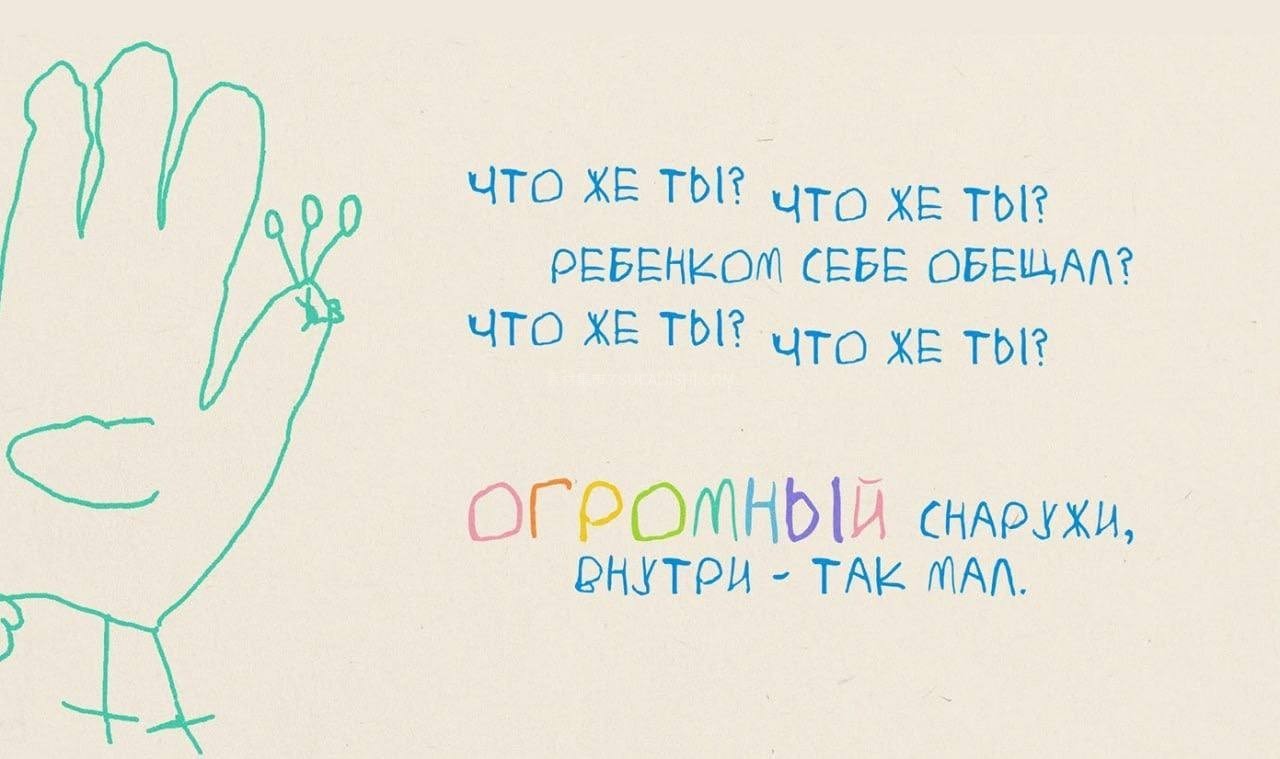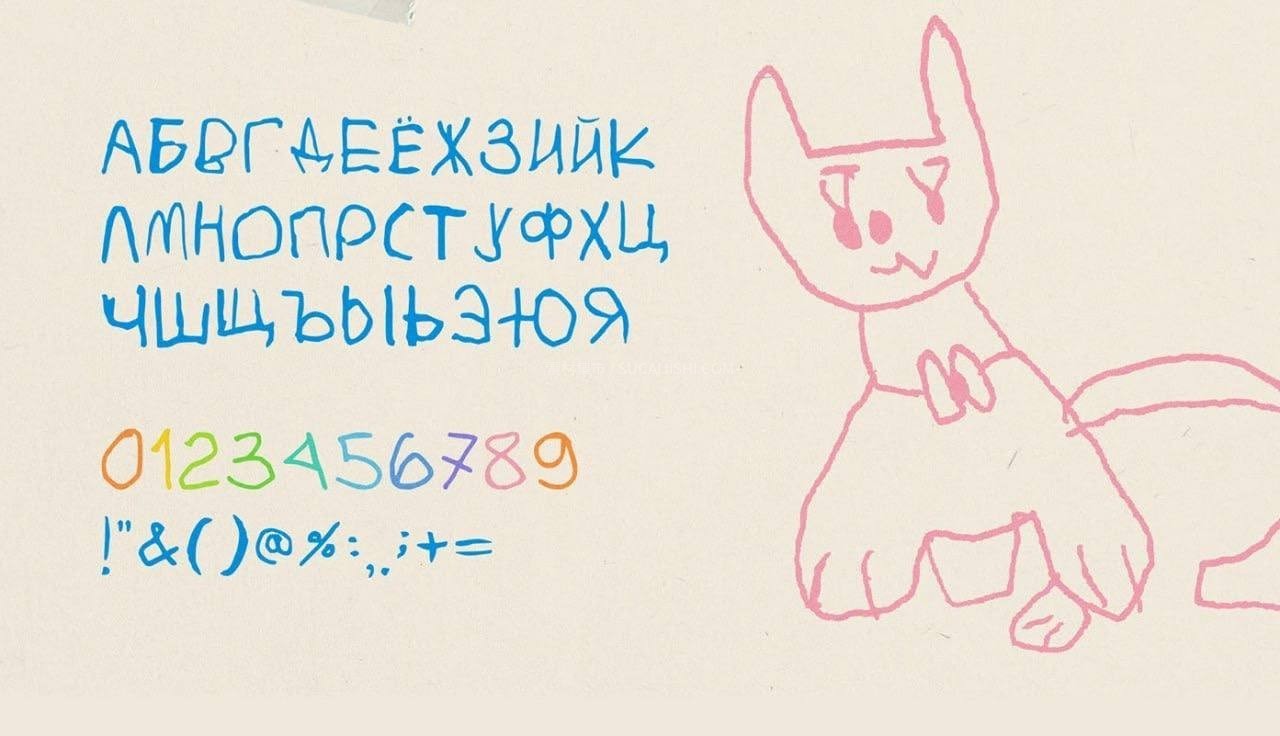
Detstvo 纯真儿童手写字体
Detstvo 是一款充满童真与温度的儿童手写体。它的灵感源自一张写给妈妈的旧新年贺卡,经过精心扫描与处理,完美保留了小朋友初学写字时那种笨拙却无比真诚的笔触。“童年”绝不仅仅是字母的组合,更是直抵人心的温暖回忆。如果你的项目需要增添一丝治愈和人情味,用它准没错!